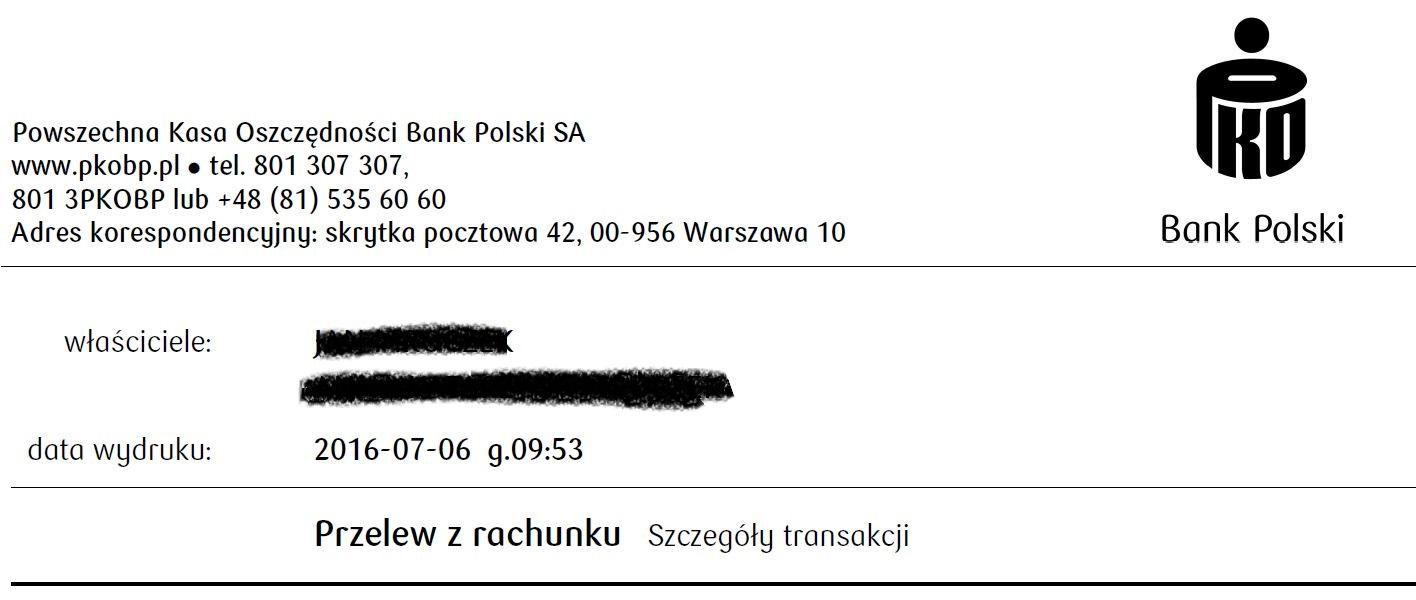
Suche diese Schrift (Bank Polski SA)
der Font wird von der Bank Polski SA verwendet. Ichhabe mich sofort verliebt...
Wer kann mir sagen, wie der Font heißt und wo ich ihn kaufen kann ?
Wahrscheinlich nirgends. Das wird die exklusive Hausschrift der Bank sein.
Ich vermute, es ist eine extrem verbastelte FF Sari. (Und sieht für meine Begriffe übrigens fürchterlich aus.)
Der Font heißt "PKOBankPolski" und ist – wie Ralf schon schrieb – eine exklusive Hausschrift.
Hätte ich auch. Nach zwölf Jahren Isolationshaft und … Spaß beiseite. Falls die Cocon eine Alternative für dich ist, könntest du auch mal einen Blick auf die Finn (Lazydogs) werfen. Ist im Gegensatz zur Cocon zwar ein wenig unausgegoren, aber dafür weniger weich.